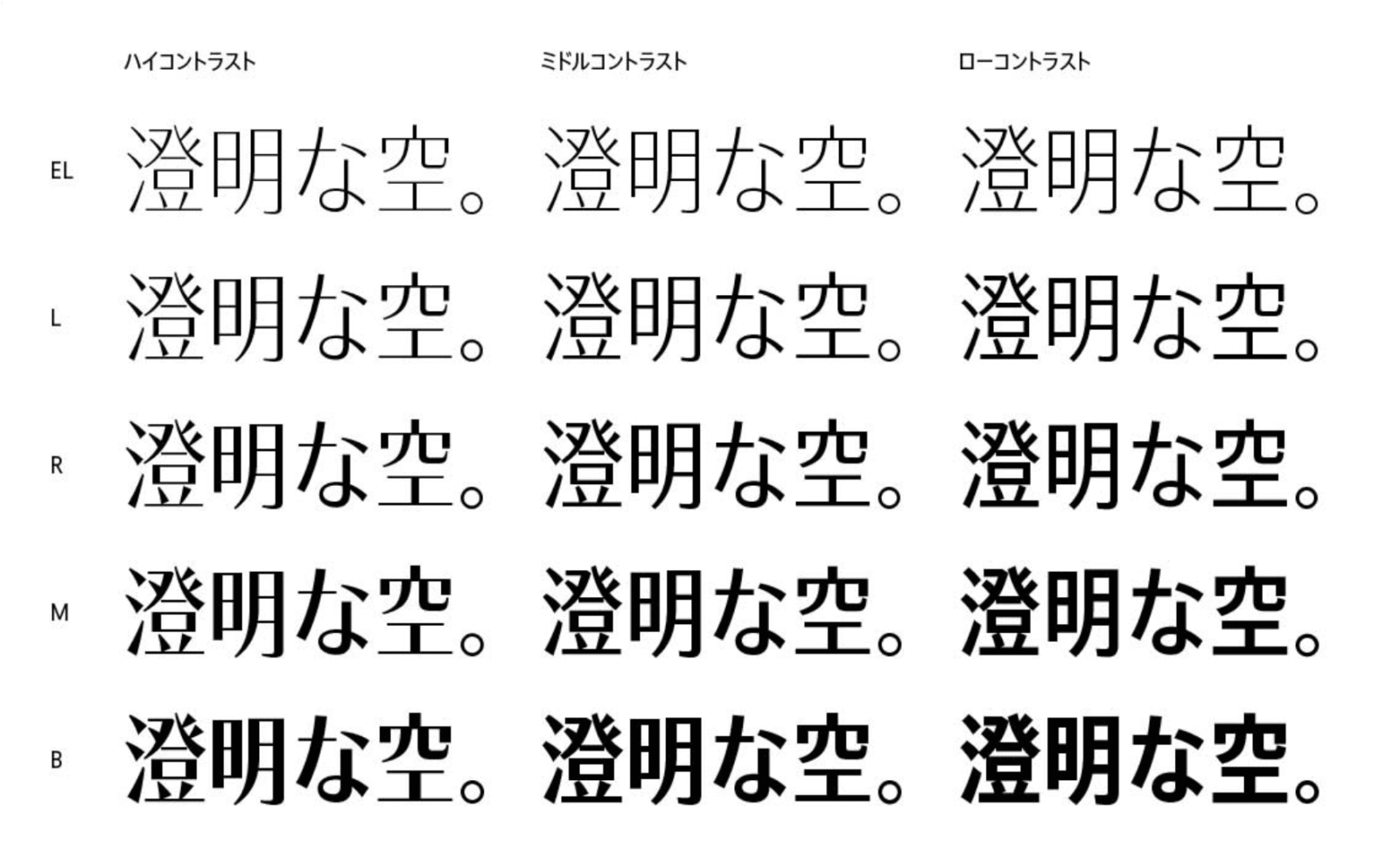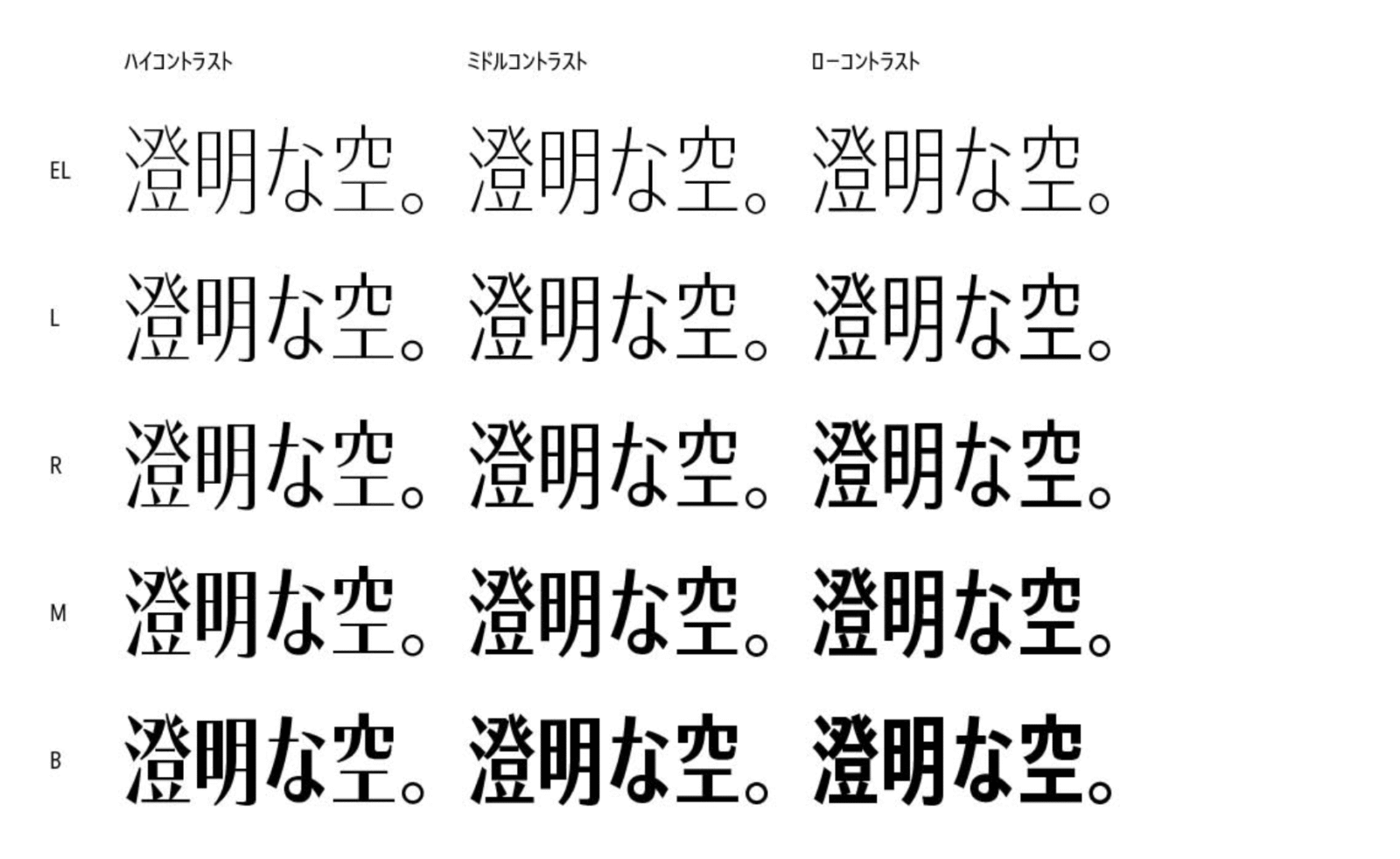
「TPスカイ コンデンス・コンプレス」発売開始
日本語フォントで初めて、ウエイト・コントラスト・字幅の 3 つの軸を提供
タイププロジェクト株式会社 (東京都練馬区 代表取締役社長 鈴木 功、以下 タイププロジェクト) は、 抑揚サンセリフ体である TP スカイの長体シリーズとして、「TP スカイ コンデンス」および「TP スカイ コンプレス」を発表し、本日より発売を開始いたします。
TP スカイ コンデンスと TP スカイ コンプレスは、ウエイト・コントラスト・字幅の 3 つの軸を持つ初め ての日本語フォントです。表示適正の高い TP スカイに長体シリーズを加えることで、美しさとともに画 面の空間効率も高め、未来のスクリーンに新たな文字表現をもたらします。
アウトラインの滑らかさに重点を置き、簡潔な文字描画によってフォントデータの軽量化を実現した TP スカイファミリーに長体シリーズが加わることで、5ウエイト、3 コントラスト、そして 3 つの字幅の全 45 フォントが揃いました。
長体でデザインした真のコンデンス体である TP スカイ コンデンスは、漢字と仮名ともに 85%の長体率で 設計し、コンプレスは 70%の長体率で設計しています。コンデンス、コンプレスともに、フォルムとカウ ンターのバランスを丁寧に整え、画線の太さと文字の黒みを徹底的に揃えることで、サンセリフ体のフォントに期待されるフラットな質感を高いレベルで実現しています。
TP スカイ コンデンス
TP スカイ コンプレス
タイププロジェクトの代表取締役 鈴木 功は、「TP スカイファミリーでは、現代日本語に頻出するカタカナの品質をとくに念入りに磨き上げました。商品や会社のロゴタイプにそのまま使えるフォントになっていますので、画面のサイズや使用目的に応じて最適なウエイトやコントラスト、字幅をお選びいただくことで、UI メニューからデジタルサイネージまで、幅広い用途にきめ細かく対応することができると自負しています。5ウエイト、3 コントラスト、そして 3 つの字幅。TP スカイファミリー全 45 フォントを十全にご活用ください」と述べています。
TP スカイは、本文と見出しやタイトルとキャプションなど、表示サイズや解像度に最適なフォントを選択することで、明朝体とゴシック体を用いることなく、高いレベルでの画面表示を実現します。ロゴをはじめ、名刺やカタログ、サイトや店舗などで使用するフォントを TP スカイで統一することで、ブランドイメージに一貫性を与えることができます。